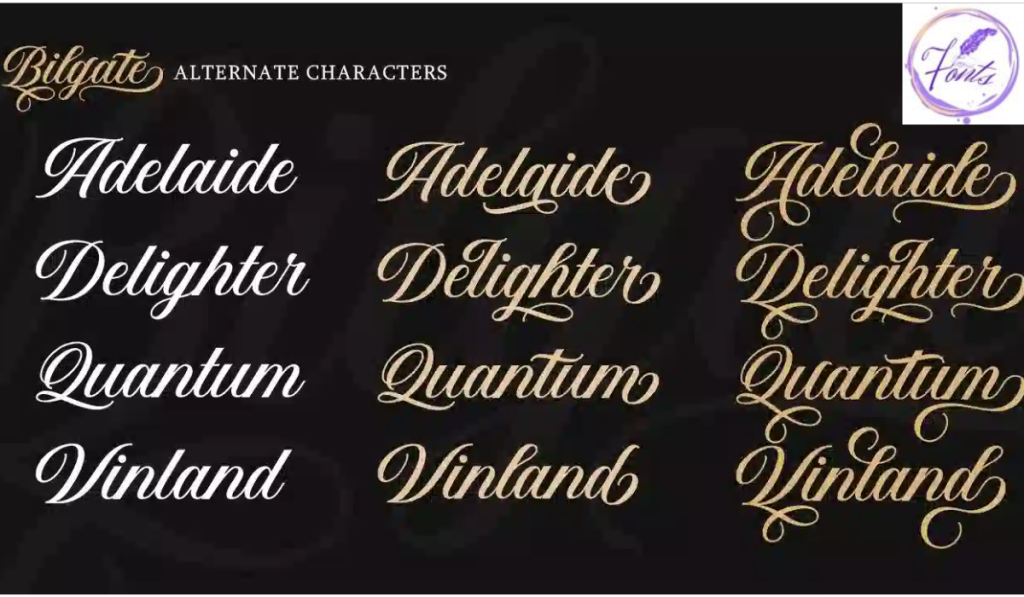
Font Calligraphy việt hóa
Font Calligraphy việt hóa mang lại vẻ đẹp của nghệ thuật thư pháp cho ngôn ngữ Việt. Sự kết hợp này không chỉ tôn vinh vẻ đẹp của từng nét chữ Việt mà còn phản ánh sự tinh tế và nghệ thuật trong mỗi thiết kế. Những font này thường được sử dụng trong thiệp mời, các tác phẩm nghệ thuật, logo thương hiệu và các ấn phẩm in ấn cao cấp, mang đến cảm giác trang trọng và duyên dáng cho người xem.
Đánh giá font calligraphy việt hóa
Nhiều nhà thiết kế đã đánh giá cao font calligraphy việt hóa vì khả năng truyền tải cảm xúc và vẻ đẹp thẩm mỹ. Những font này không chỉ giúp tăng tính thẩm mỹ cho các sản phẩm mà còn giúp các thông điệp trở nên có hồn và ấn tượng hơn. Sự phong phú về kiểu dáng và tính linh hoạt trong ứng dụng làm cho chúng trở thành một lựa chọn phổ biến cho những dự án cần sự sang trọng và quý phái.